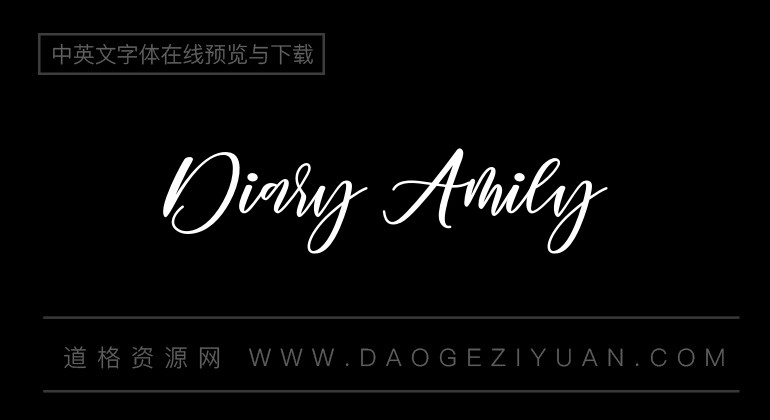
吧? Diary Amily 是一款英文手写体字体,由著名的设计师Maria Grønlund设计,它具有温暖、柔和、可爱的特点,可以用来做各种卡片、封面、海报、标识等设计,也可以用在博客、社交媒体等场景。它具有独特的手写体表现力,可以创造出精致、温馨的设计效果。内容介绍
Diary Amily是一款非常不错的手写艺术字体,具有很好的视觉感,适合于文化类的宣传设计、商业类品牌的广告和产品包装设计以及个性化文字排版等较多场景。